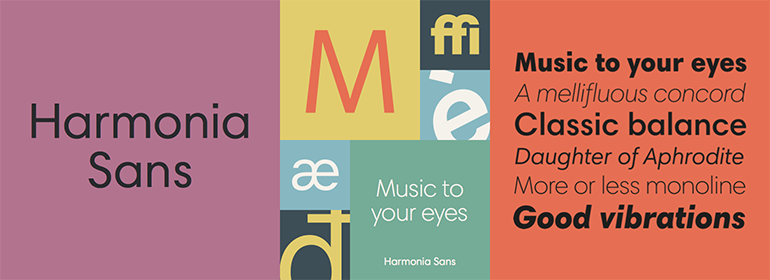
Harmonia Sans™
Harmonia Sans™,这款字体结构工整、笔画清晰,兼顾美观与易读性,适用于标题、正文、海报、包装、LOGO 等多种场景。字形优雅稳定,风格百搭耐看,适配日常排版与创意设计,让文字呈现更舒适、更具质感。Harmonia Sans™一笔一画,皆是细节,以均衡的比例、流畅的线条打造舒适视觉体验,字形端正大气,风格简约现代。无论是商业设计、品牌宣传还是日常排版,都能轻松驾驭,让文字更有格调与力量。Harmonia Sans™字体下载。
字体品牌: Monotype 设计师:Wasco,Jim 字体分类:无衬线体 字体属性:外文 字符集:Unicode 发布时间: 2018